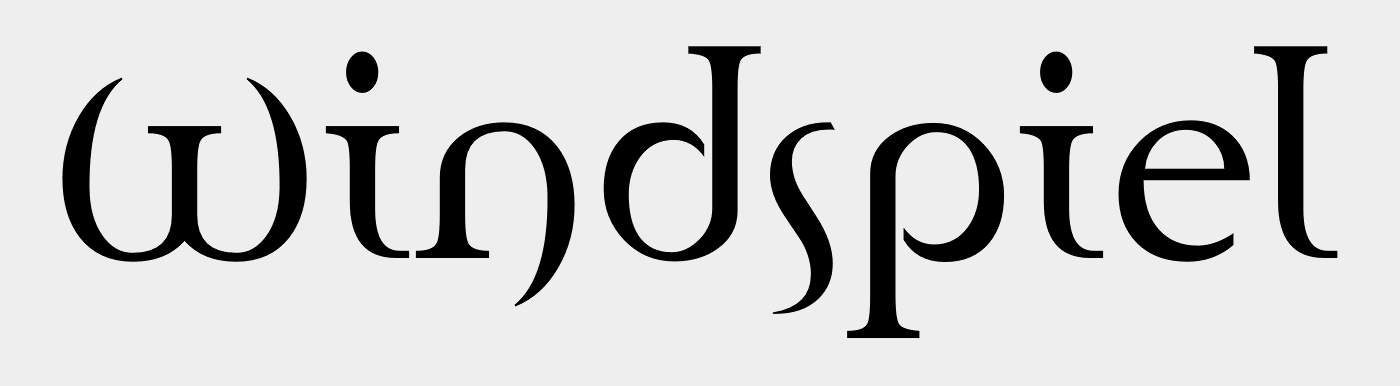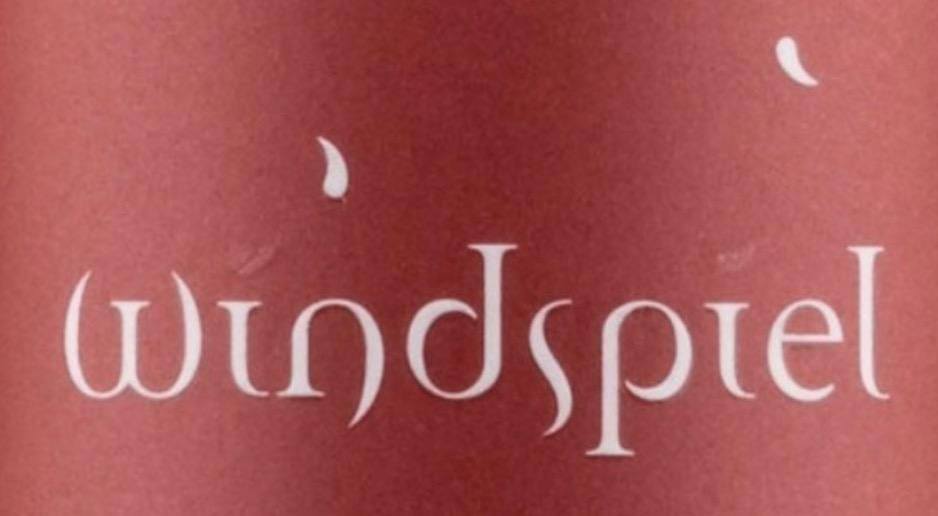
Schriftart vom Wein »windspiel« gesucht
Vor etwa 5 Jahren fotografierte ich folgendes Ettiket einer Weinflasche. Der Zweigelt stammte vom Weingut Fritsch aus Niederösterreich. Bis jetzt habe ich die Schrift noch nicht gefunden. Und weil die Suche hier im Forum so fantastisch geklappt hat, probier ich´s gleich nochmal. Mir gefällt die Schrift, wo ich diese dann einsetzen kann, wird  sich bestimmt beim herumspielen mit den Zeichen zeigen.
Nachtrag: Habe die Schrift nochmal bei MyFonts gesucht und tatsächlich gefunden. Das Erkennungsprogramm spuckte die »Envision« aus. Leider gefallen mir viele der anderen Zeichen nicht. Dort sieht´s aus wie eine Schrift eines andern Planeten. Schade.
Sind das Kommas, "gone with the wind" ?